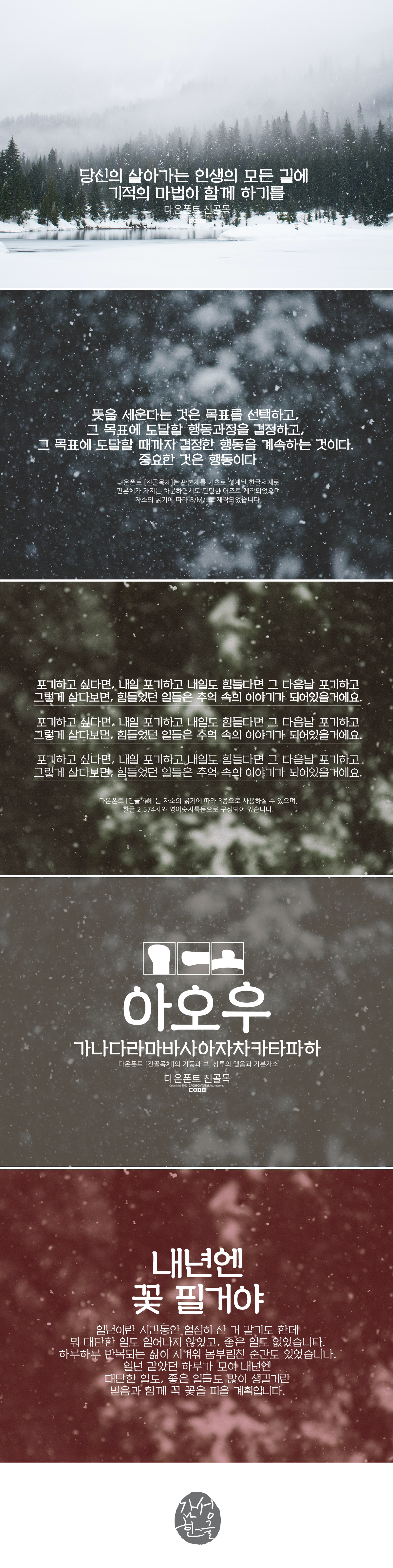
12월 신서체 다온폰트 진골목 출시안내
12월 신서체인 다온폰트 "진골목"이 업데이트 되었습니다.
다온폰트 "진골목"은 판본체를 기초로 설셰된 한글서체로
판본체가 가지는 차분하면서도 단단한 어조로 제작되었습니다.
한글 2,350+430와 영어,숫자,특문으로 구성된 폰트로
자소굵기에 따라 B/M/L 3종으로 제작되었습니다.